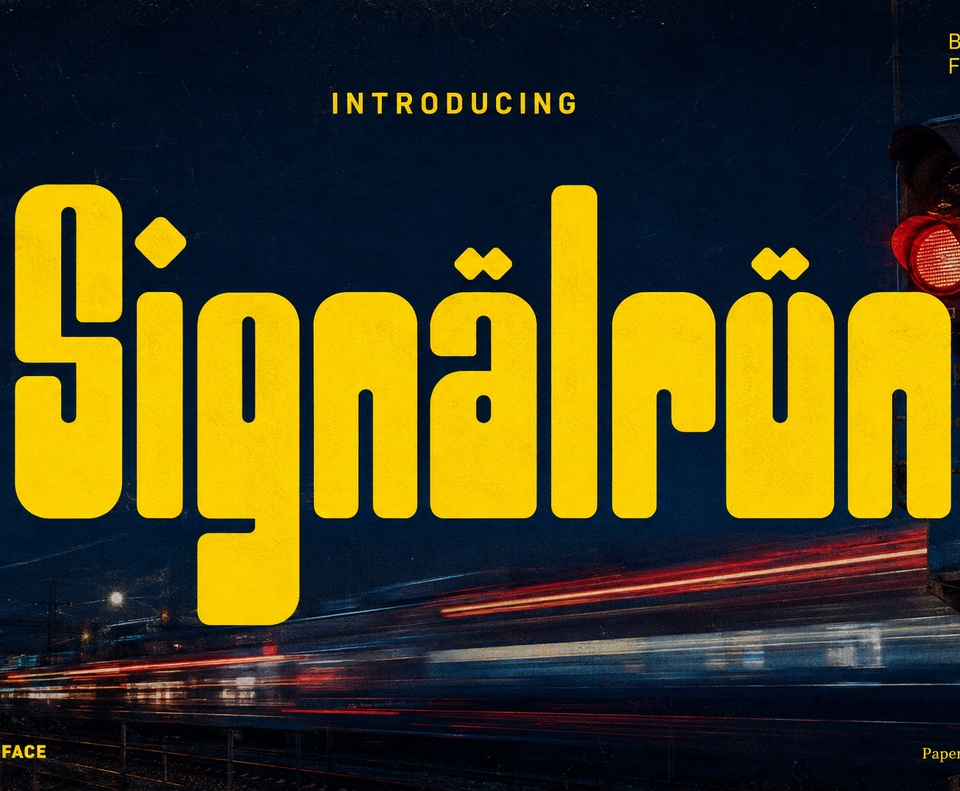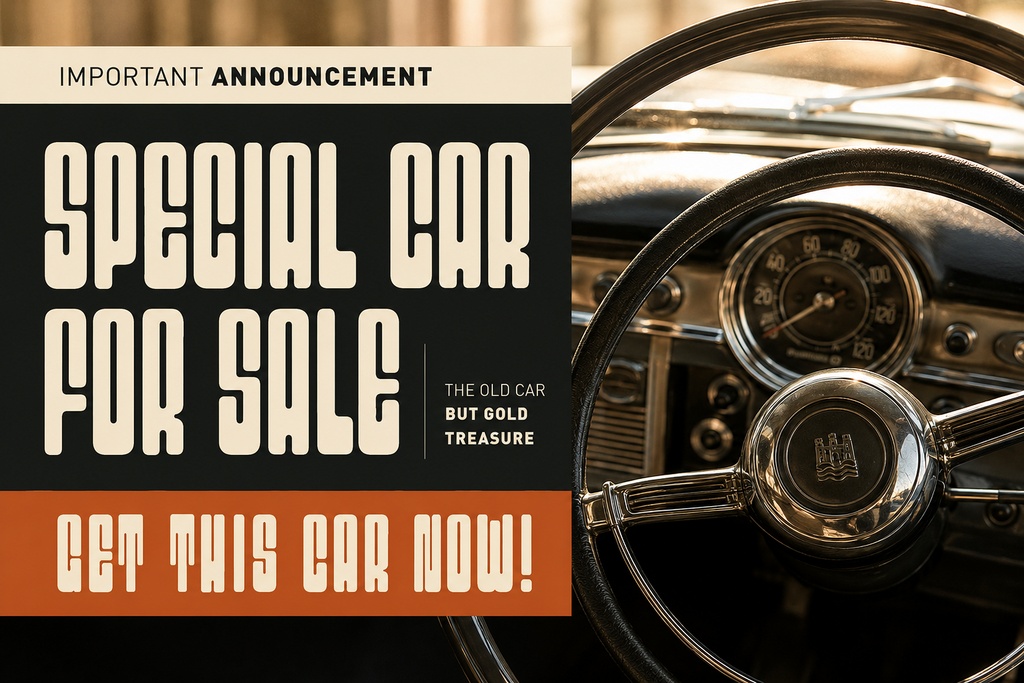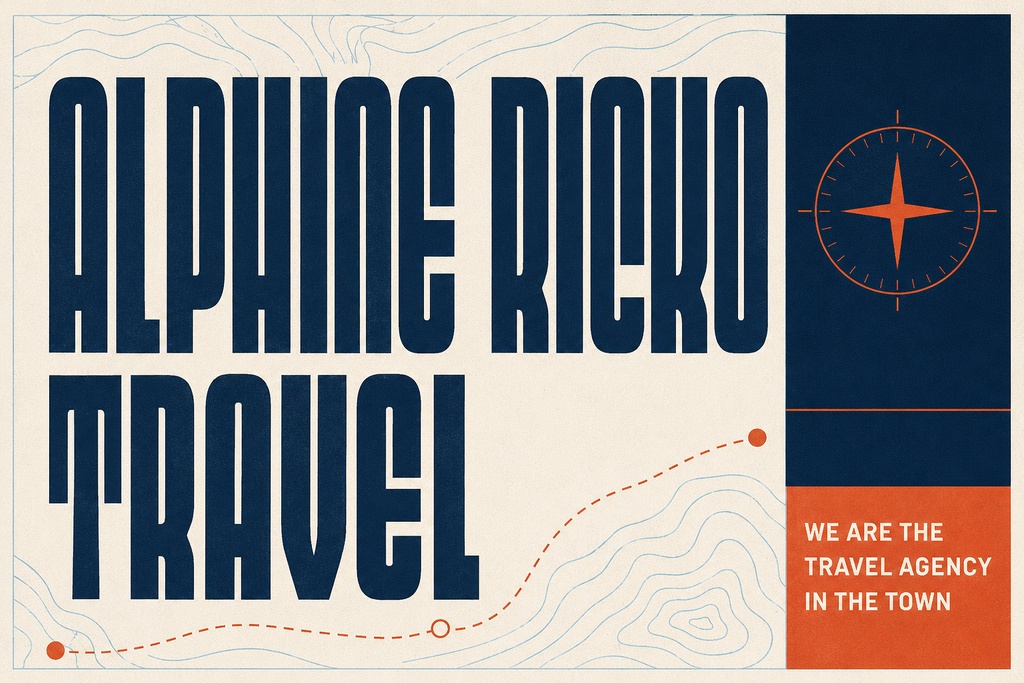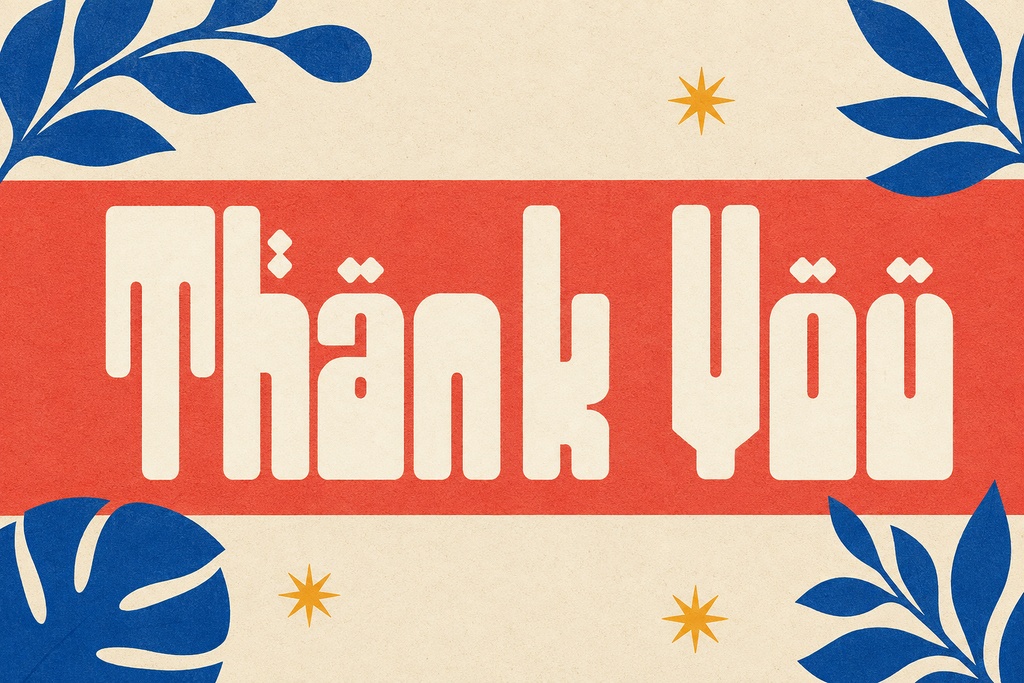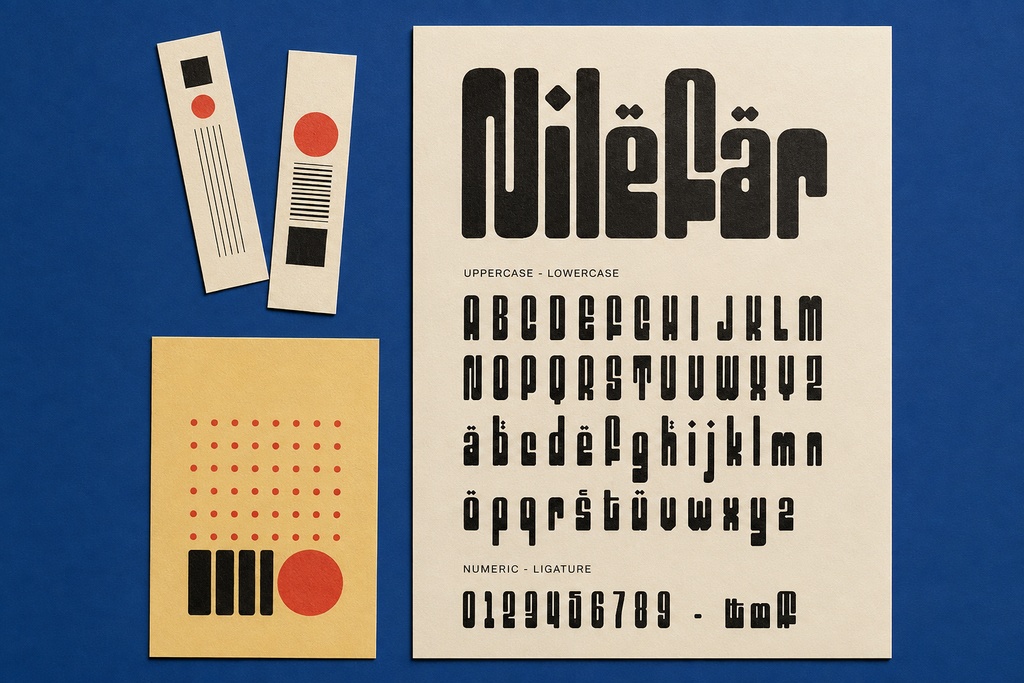
Signalrun — ブランディングやポスターに最適な太字ディスプレイフォント
**Signalrun**は、表現力豊かでインパクトのある個性的なディスプレイフォントです。力強く自信に満ちたデザインは、見出し、ロゴ、ブランディング、ポスター、パッケージなど、一言で注目を集めたいプロジェクトに最適です。レイアウトに大胆で印象的なビジュアル表現や、記憶に残るタイポグラフィを取り入れたいときに活躍する見出し用フォントです。 ### これはどんなフォント? Signalrunは、力強いデザインと237グリフを収録した**Regularウェイトのディスプレイ書体**です。大文字・小文字、記号・句読点、数字、リガチャ、オルタネート、そして多言語サポートを含んでいます。表現力豊かな文字形により、ディスプレイフォントならではの強い視覚的インパクトを保ちながら、ロゴやブランドアイデンティティ制作にも実用的な太字書体として使用できます。 ### 主な特徴 OpenTypeフォントには、文字表現に変化や個性を加えられる**リガチャとオルタネート**が含まれています。大文字と小文字の両方に対応しているため、ロゴ、タイトルデザイン、エディトリアルレイアウト、ポスターなどで柔軟な文字階層を構築できます。数字、記号、句読点も収録されているため、文字だけに頼ることなく、完成度の高い見出しやタイポグラフィを作成できます。 多言語サポートにより、ラテン文字を使用するさまざまな言語のプロジェクトで活用できます。237グリフの文字セットは、一般的なディスプレイデザインやブランディングに必要な文字を幅広くカバーしています。また、Signalrunは**Webフォントにも対応**しているため、印刷物からデジタルアプリケーションまで、統一感のあるビジュアルスタイルを展開できます。 ### 使用用途 個性的なロゴデザイン、力強いブランドアイデンティティ、イベントポスター、キャンペーン用見出し、エディトリアルカバー、商品ラベル、パッケージデザイン、アパレルグラフィック、SNS用グラフィック、ゲームやエンターテインメントのタイトルなど、幅広い用途に使用できます。 Signalrunは、短いフレーズ、名前、大型タイポグラフィなど、表現力豊かな書体と強い存在感が求められるデザインで特に効果を発揮します。Webサイトのヒーロー見出し、デジタルバナー、その他のディスプレイテキストにもエネルギーと個性を加えることができます。 ### 対応形式 パッケージには以下のフォント形式が含まれています。 * **OTF** — OpenType Font * **TTF** — TrueType Font * **WOFF** — Webfont * **WOFF2** — Webfont OTFとTTFは、インストールしたフォントに対応するデスクトップデザインや印刷制作に使用できます。WOFFとWOFF2は、Webフォントの埋め込みに対応したWebサイトやデジタルインターフェース向けの形式です。プロジェクトや使用するソフトウェアに適した形式をご利用ください。 ### ライセンス **Cubebrush Commercial License**は、クレジット表記なしで商用デザインや商用プロジェクトに使用するためのライセンスです。フォントファイルの再配布、ソフトウェアへの埋め込み、またはフォントそのものを主要なアセットとする商品の制作を行う場合は、利用前にCubebrushの最新のライセンス規約をご確認ください。 アップローダーによって提供されている場合、**Basic License**は個人利用または非商用目的にのみ適しています。 次のロゴ、ポスター、パッケージ、ブランディングプロジェクトに、**Signalrun**の自信に満ちた大胆なディスプレイ表現を取り入れてみましょう。